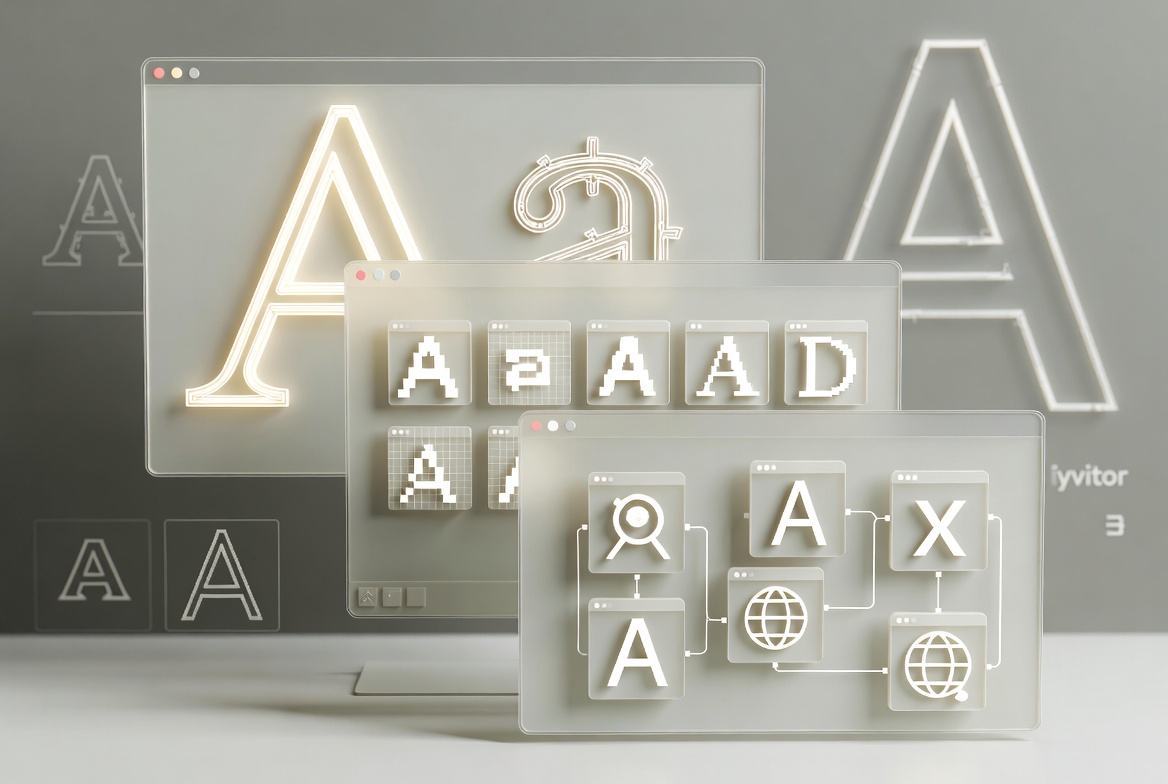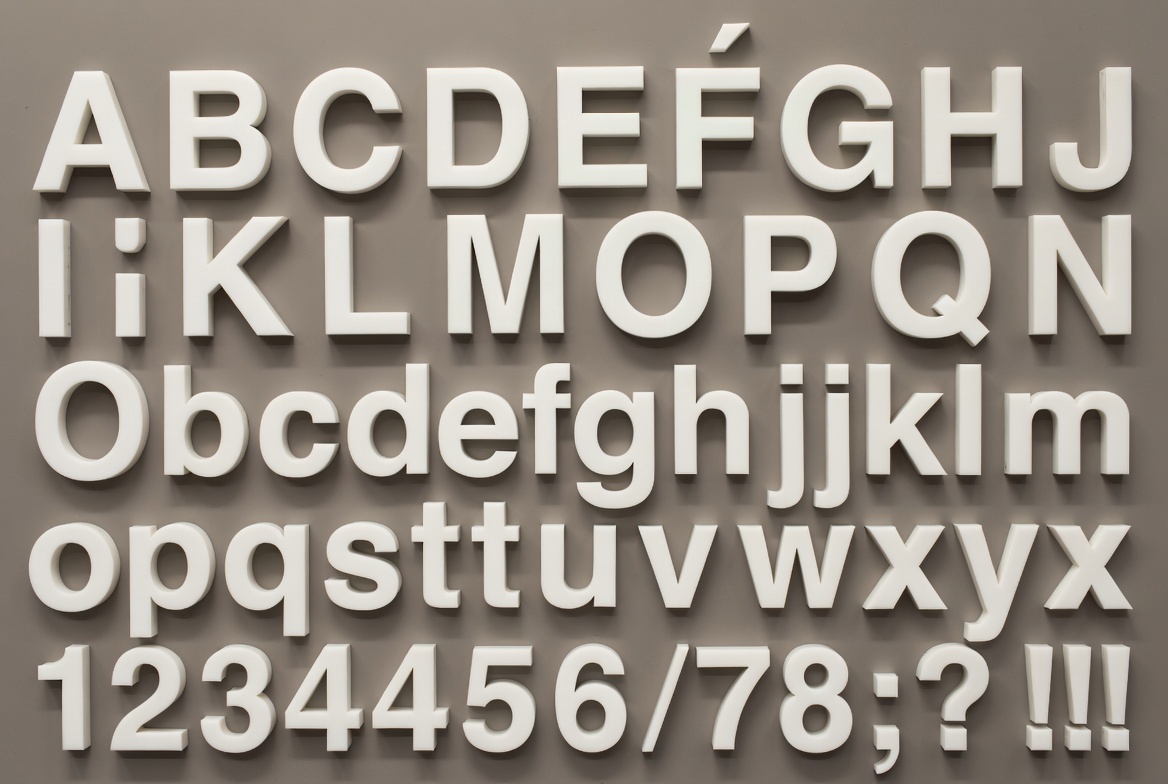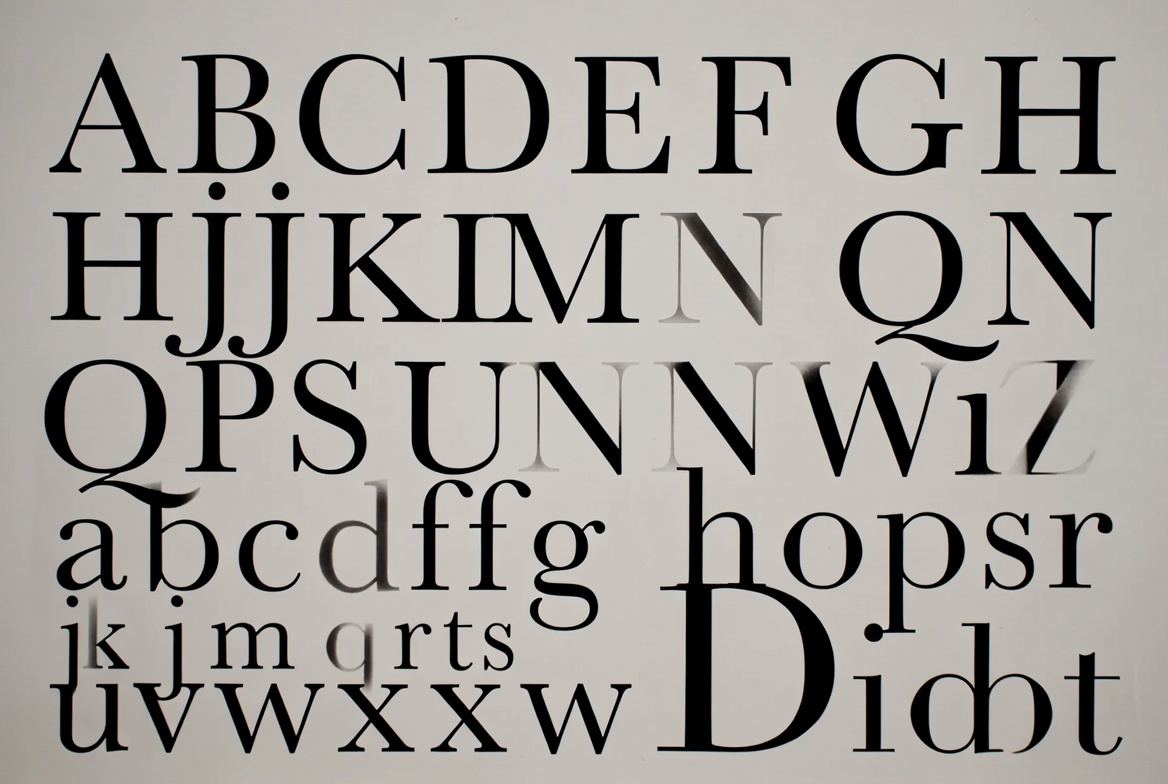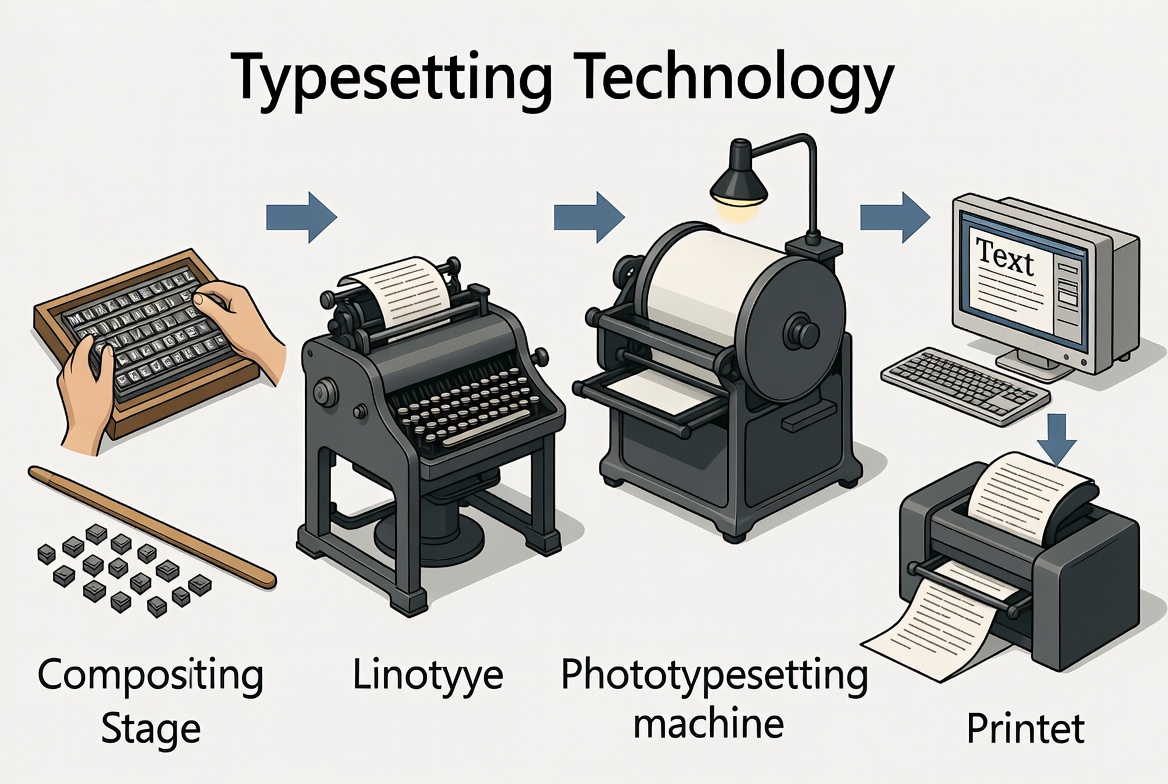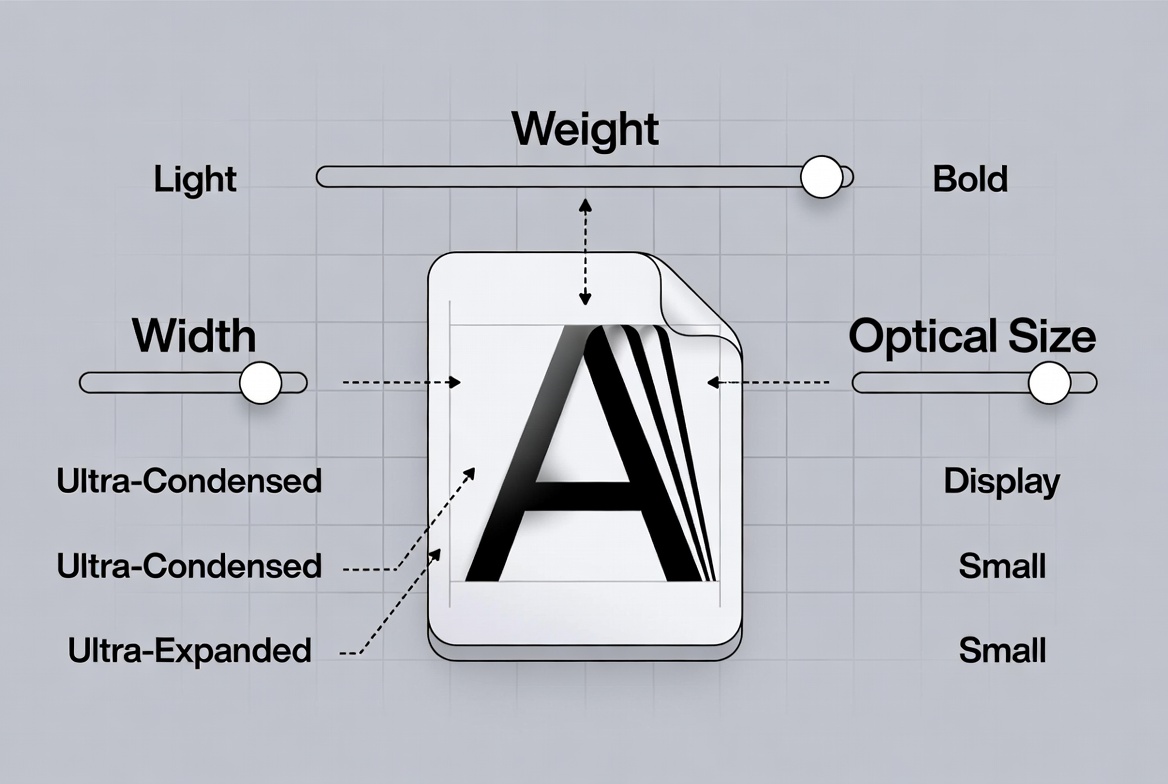
Geschichte der Schrift – Teil 4: Moderne Schriften und Typografie
Von den klassizistischen Antiquas über die serifenlosen Schriften bis zur digitalen Typografie – die Entwicklung der Schrift vom 18. Jahrhundert bis heute.
Mit dem Buchdruck war die technische Grundlage für die moderne Schriftentwicklung gelegt. Ab dem 18. Jahrhundert veränderte sich das Schriftbild erneut grundlegend – und mit der Digitalisierung im 20. und 21. Jahrhundert wurde Schrift endgültig zu dem Medium, das wir heute täglich nutzen.
Klassizismus und die neuen Antiquas
Im 18. Jahrhundert entstanden Schriften, die sich klar von den älteren Renaissance-Antiquas unterschieden. Besonders einflussreich waren:
- John Baskerville (England)
- Giambattista Bodoni (Italien)
- Firmin Didot (Frankreich)
Illustration klassizistischer Antiquas (Baskerville, Bodoni, Didot)
Diese sogenannten klassizistischen Antiquas zeichnen sich durch starken Kontrast zwischen Haar- und Schattenstrichen, senkrechte Achsen und feine, oft unbracketed Serifen aus. Sie wirkten eleganter und moderner als ihre Vorgänger und prägen bis heute viele Bücher und Magazine.
Das Zeitalter der serifenlosen Schriften
Im 19. Jahrhundert kamen die ersten serifenlosen Schriften (Sans-Serif) auf. Zunächst wurden sie vor allem für Überschriften und Werbeanzeigen verwendet. Im 20. Jahrhundert entwickelten sie sich zu den beherrschenden Schriften der Moderne.
Wichtige Meilensteine waren:
- Akzidenz-Grotesk (Ende 19. Jahrhundert)
- Futura (Paul Renner, 1927)
- Helvetica (Max Miedinger, 1957)
- Univers (Adrian Frutiger, 1957)
Illustration der Schrift Helvetica
Besonders Helvetica wurde zu einer der einflussreichsten Schriften des 20. Jahrhunderts und steht bis heute stellvertretend für klare, neutrale und funktionale Typografie.
Industrialisierung und neue Satztechniken
Mit der Industrialisierung stieg der Bedarf an vielfältigen und auffälligen Schriften enorm. Gleichzeitig veränderten sich die Satztechniken:
- Vom Handsatz zum Maschinensatz (Linotype, Monotype)
- Später zum Fotosatz
- Und schließlich zum digitalen Satz
Illustration der Entwicklung vom Handsatz über den Maschinensatz und Fotosatz bis zum digitalen Satz
Jede dieser Techniken beeinflusste, welche Schriften möglich und wirtschaftlich sinnvoll waren.
Die digitale Revolution
Ab den 1980er-Jahren veränderte die Digitalisierung die Schriftwelt von Grund auf. Wichtige Schritte waren:
- PostScript (Adobe) und die Möglichkeit, Schriften auf dem Computer zu erzeugen und zu nutzen
- TrueType und später OpenType
- Die Verbreitung von Desktop-Publishing
- Die Entwicklung von Webfonts, die Schriften direkt im Browser darstellbar machten
Illustration der digitalen Schrifttechnologien: PostScript, TrueType/OpenType und Webfonts
Heute stehen uns Tausende von Schriften digital zur Verfügung. Gleichzeitig sind Fragen der Lizenzierung, der Qualität und des professionellen Font-Managements wichtiger denn je – genau die Themen, mit denen sich FontFlux beschäftigt.
Schrift heute
Die aktuelle Typografie ist geprägt von:
- einer enormen Vielfalt an Schriftarten
- Variable Fonts, die mehrere Schnitte in einer Datei vereinen
- hohen Anforderungen an die Lesbarkeit auf Bildschirmen
- der Notwendigkeit, Schriften rechtssicher und effizient zu verwalten
Illustration des Konzepts von Variable Fonts
Die Geschichte der Schrift ist damit nicht zu Ende. Sie geht weiter – nur eben digital, vernetzt und in einem Tempo, das die Schreiber der Keilschrift oder die Mönche des Mittelalters sich nicht hätten vorstellen können.
Schluss
Von den ersten Verwaltungszeichen in Mesopotamien über das Alphabet, die mittelalterlichen Handschriften und den Buchdruck bis zu den Schriften auf unseren Bildschirmen spannt sich ein weiter Bogen. Schrift war und ist nie nur Technik – sie ist Ausdruck von Kultur, Macht, Wirtschaft und Kommunikation.
Wer Schriften versteht und bewusst einsetzt, arbeitet mit einem der ältesten und zugleich modernsten Werkzeuge der Menschheit.